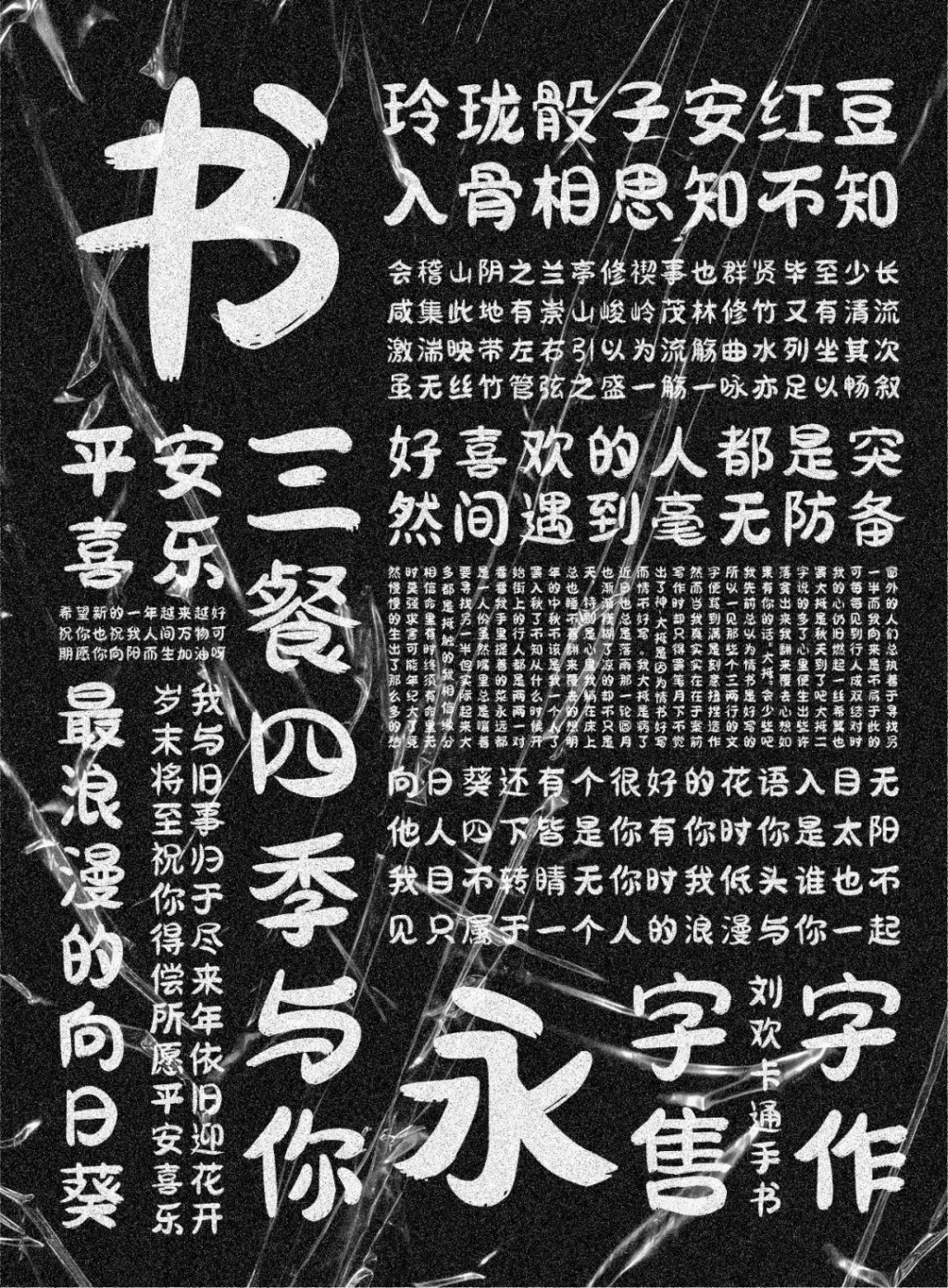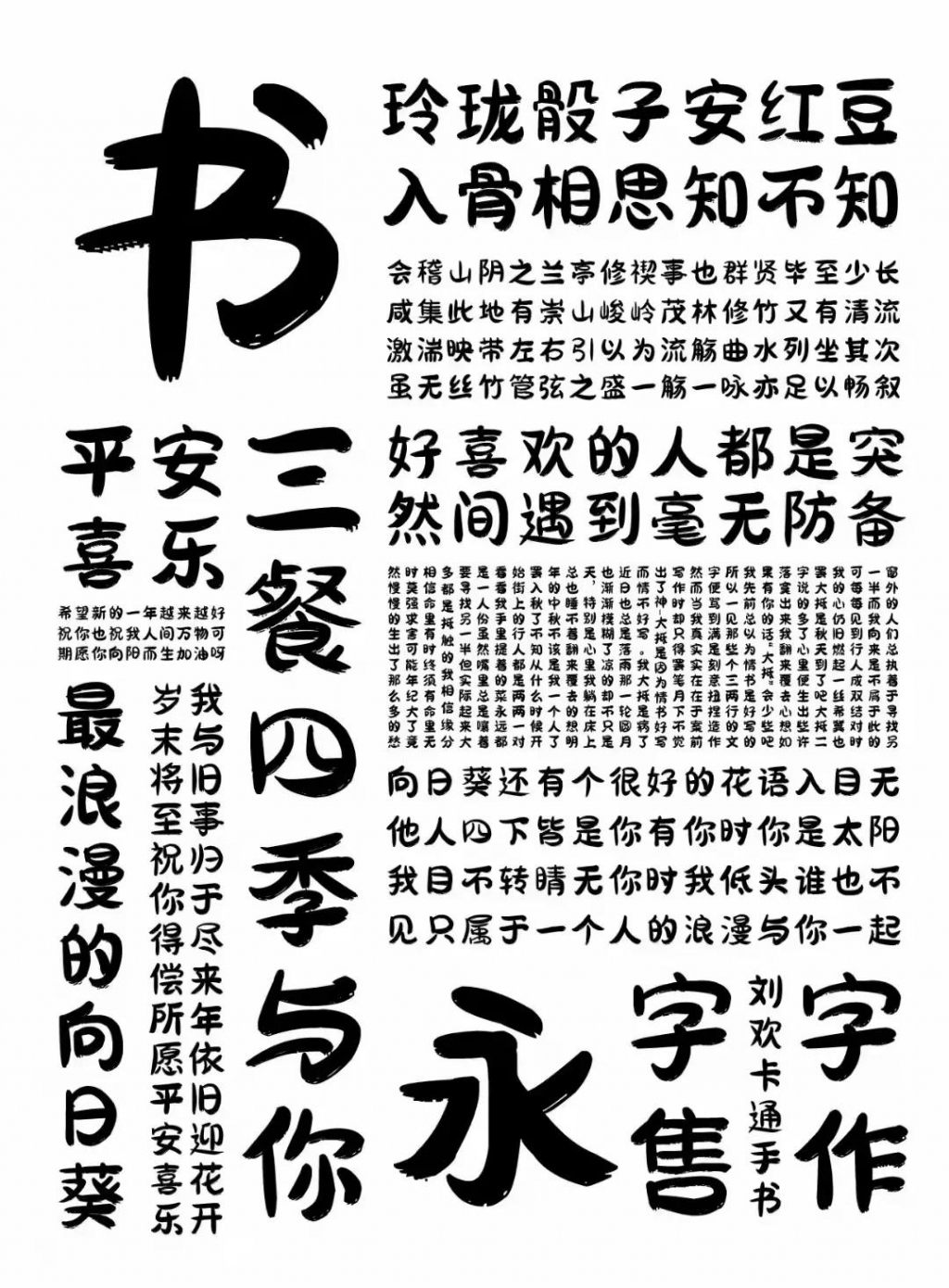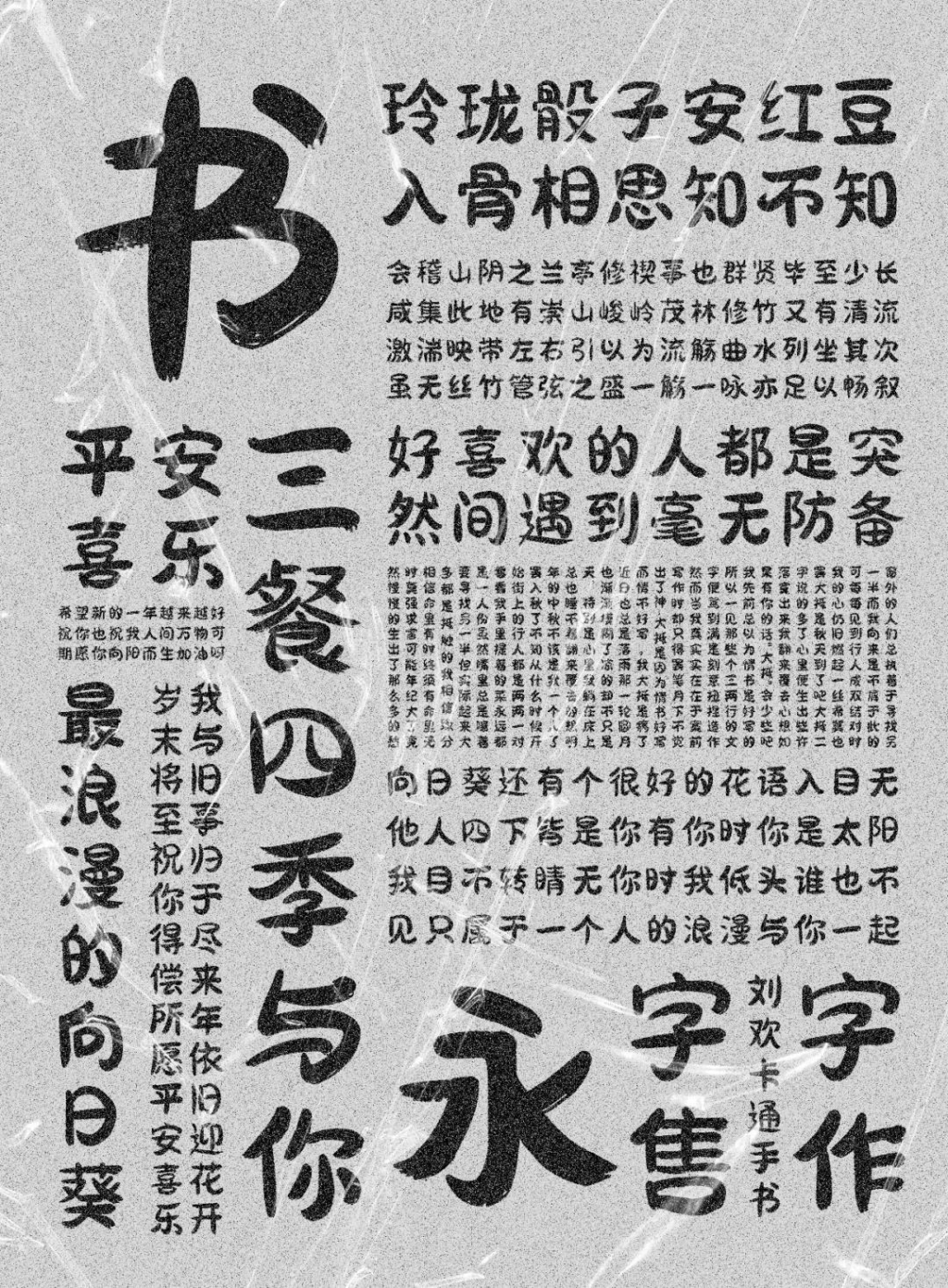
2018年初,接触到字体设计,就被汉字的演变深深吸引,一向不爱写字的我才发现:原来汉字还可以这么美!
其实说起这套字库的创作初衷,是因为当时找的工作不合适然后回家了…
当时实习选择去了离家还算近的上海。全球最现代化的大城市之一,纸醉金迷的大上海,繁华程度已经超过东京和纽约。土狗进城,见到了很多新奇的事物,不愧是很多年轻人向往的魔都!
一个没见过世面的农村小伙子,见到了繁华的夜都市和车水马龙,以及熙熙攘攘的业界精英。我也想过在上海拼搏闯出一片属于自己的小天地,奈何实力不济,上漂了不到两个月,找不到自己适合的工作,最终还是回家了。
与其说,不合适,其实还是自己没有足够的实力,哈哈。也许,每个有血性的年轻人都是这样吧,见到了大城市的繁华又怎么甘心回到小县城呢。
到家以后,父母和亲戚都为我的工作而着急,都21岁了天天待在家里,邻居会怎么看?我想要提升自己的水平方便以后找工作,就以考完驾照再出去的理由在家顺利待了一段时间。
就是那段时间,在家疯狂恶补版式、插画、剩下时间就是练字了。
事实证明,在家待久了,确实被邻居嘲笑了……然后父母也不能理解自己。不出去找工作,每天在家乱写乱画的有什么用,为此也争吵了很多次……
沟通不了,还是想着能提升自己最好。继续待在家里!也可以说是写字让我有了对未来憧憬的动力。
说起字库,对于知识产权,版权问题是不可避免的,刚入门的设计师,难免会因为不懂版权,对自己或对公司而言,这几年的版权新闻巨额罚款也是不断出现,造成不可挽回的损失。想着写了就写一套字库出来,也算为社会尽自己的绵薄之力。
既然决定了就开始,每天除了吃饭就待在屋里写字,顶着压力,写了又写,改了又改,写了几种字样,最后定了这一款卡通字体。到2020年12月初全部写完。
到月底拿着自己的这套字库在测试的时候,开心的一整晚没睡着!
现在只想对当时的自己说:孤独是常有的,兴趣和理想却不是,小时候的梦想好多好多,现在你还记得吗?一个人前行时,什么都可以丢弃。目标不能丢,耐受不了寂寞,咸鱼翻身的机会都少有。
废话不多说了,我们简单认识一下作者。
简短有效的自我介绍:姓名:刘欢。年龄:23岁。母胎solo,不会才艺,这里就不表演了。
娱乐活动很少,一般都是宅在家,偶尔听听相声,看看综艺。(今年希望能够顺利脱单吧,暴富也行,哈哈哈…)
下面来看字体展示,起名“卡通”字体,其实用作“标题字”也是OK的。
所有笔画以“圆润”为主,保留少量飞白,在屏幕上显示更佳。同时在线下使用也不缺失手写韵味。该字库不限制使用场景,印刷书籍除外,不适合太小的字体展示。
这款字体以“卡通”为名,笔画有着浓浓的毛笔味,但不属于书法字体类别。字体笔画以“圆润”为主,保留少量的飞白,在字号大的时候显示更显手写的韵味。
字体中的部件“囗”以“竖+大圆弧”的形态出现,让字体显得活泼俏皮。除了印刷书籍等太小的场合不适用,该字库基本可以适用于所有使用场景,这是一款揉合了传统意味的现代标题字体。